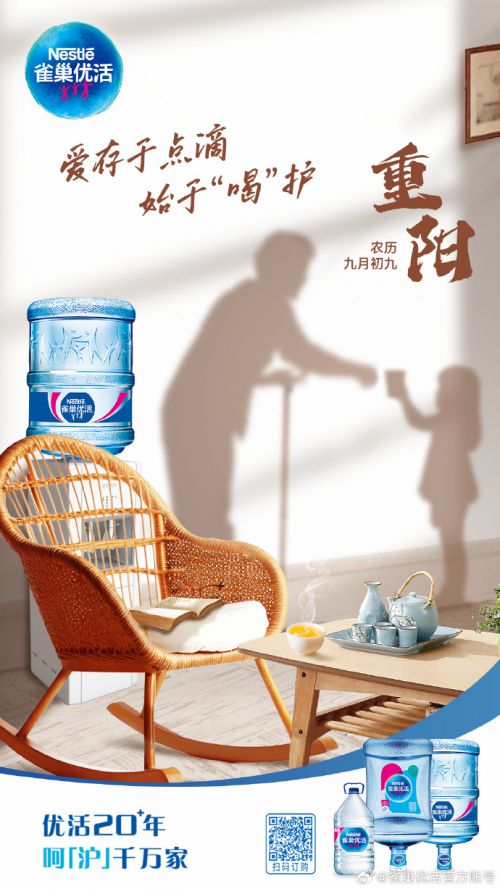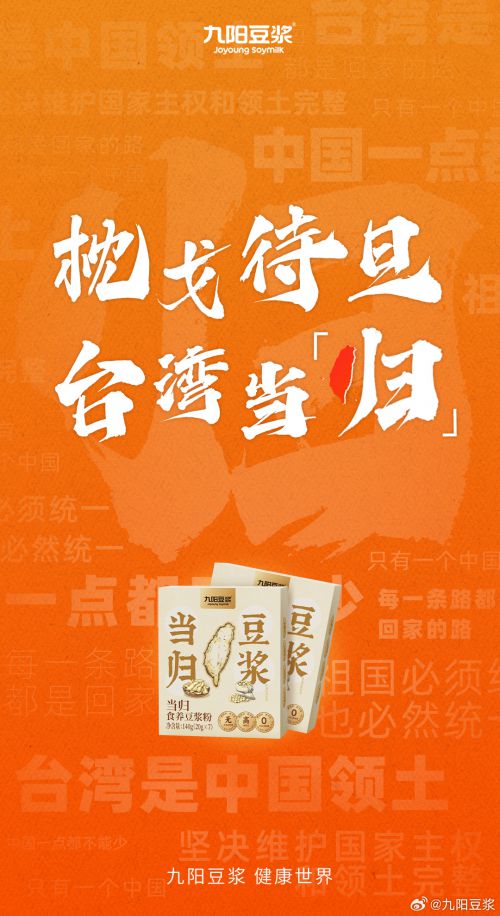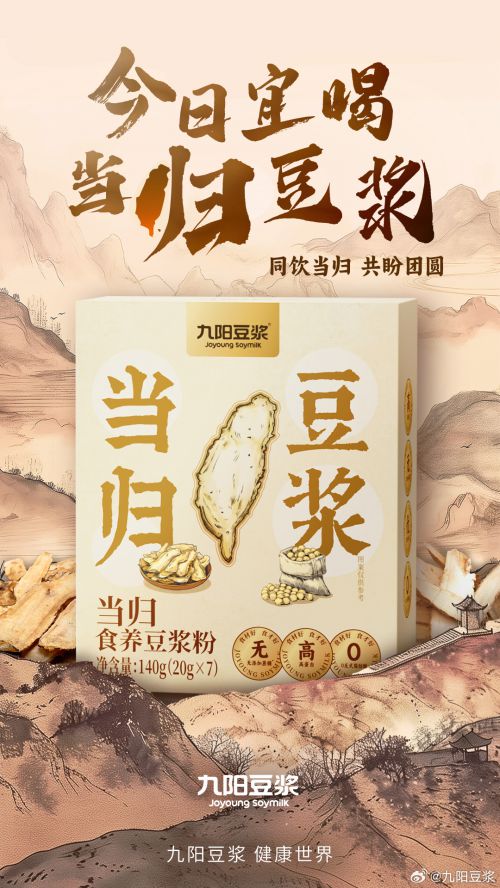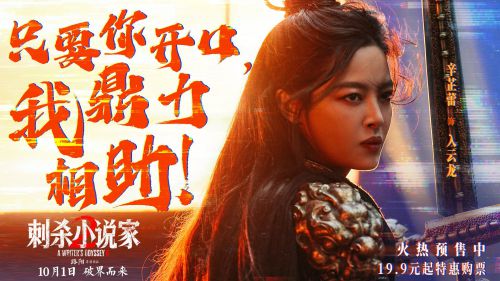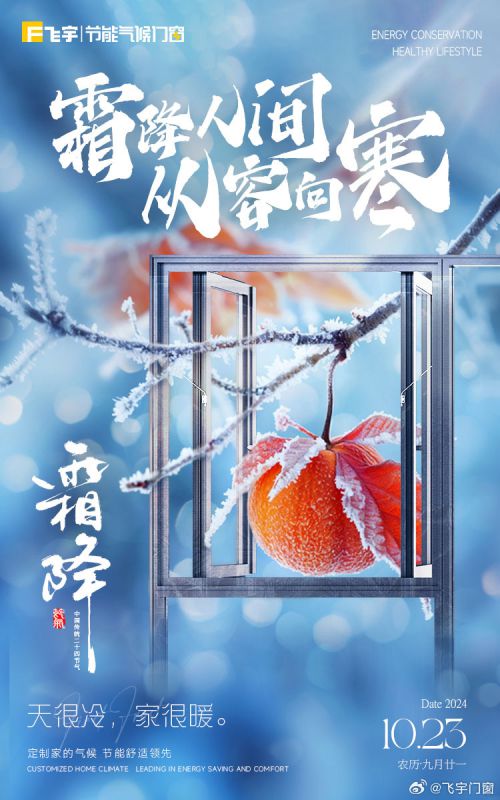
点字乘风体
点字乘风体是一款融合了古典韵味与现代美学的创意中文字体。其设计灵感源于“乘风破浪”的意境,将书法笔势的飘逸灵动与现代字体的结构清晰度巧妙结合。字体笔画流畅舒展,字形结构开放而不失平衡,整体呈现出一种自由、轻盈、富有动感的视觉效果,是一款充满艺术气息与活力的现代书法风格字体。“野水参差落涨痕,疏林欹倒出霜根”。用笔没有过分轻重,而是在结构中强调“影渐疏”。书写节奏起承转合闲适自得。